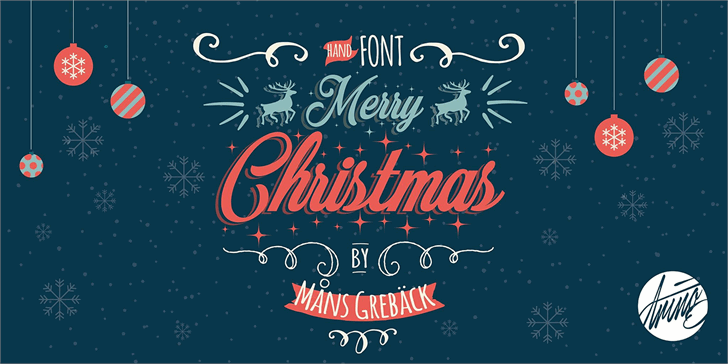
Merry Christmas font – Fonte Grátis
Merry Christmas font
A fonte “Merry Christmas” é uma elegante fidalguia desenvolvida pelo designer Hamilton. Suas linhas finas e delicadas são perfeitas para adornar cartões de Natal, letras gaudiosas em jornais ou qualquer projeto que exige um toque especial nesse momento de encantamento. Com uma arquitectura cuidadosamente pensada, essa fonte mantém seu estilo gráfico minimalista ao mesmo tempo em que transmite um caloroso bem-estar e encanto. O design perfeito para criar mensagens de Natal memoráveis e agradáveis para seus clientes ou seguidores, “Merry Christmas” é uma escolha inteligente para aqueles buscando algo único e eficaz para o seu portfolio de fontes. Para quem deseja adquirir um uso comercial desta linda fidalguia, visite a página do designer onde encontrará todos os detalhes que precisa.